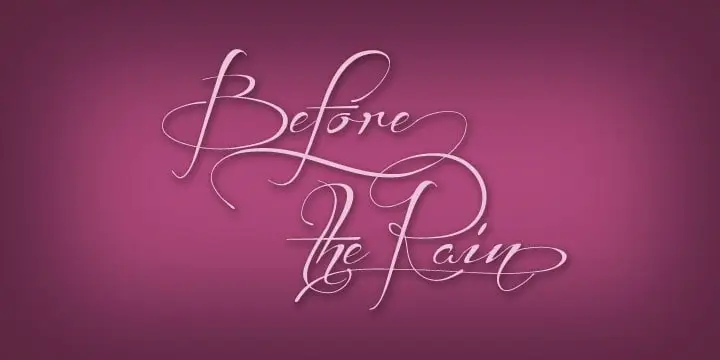
Before The Rain Font – Fonte Grátis
Before The Rain Font
Aqui está uma breve descrição do estilo envolvente e natural da fonte ‘Before The Rain Font’ para a categoria de Script Fonts: Imagine uma fonte de letra script que toca um delicado som de chuva antes de começar. A ‘Before The Rain Font’, criada por Hamilton, é uma composição suave e fluida perfeita para criar letras cheias de emoção. Ela transmite calma e sutileza através da sua forma arredondada e agradável ao olho. Ainda que simplesmente delicada, esta fonte carrega com ela o encanto de uma atmosfera relaxante antes da chegada do sol, ou como se fosse um prelúdio para qualquer tipo de expressão artística. Ideal tanto para criações digitais quanto para trabalho impresso, a ‘Before The Rain Font’ é uma escolha perfeita para aqueles que procuram uma fonte de qualidade para seus trabalhos pessoais e comerciais. Aqui está o endereço onde você pode encontrá-la: http://www.mansgreback.com. Não hesite em entrar em contato  se tiver alguma questão ou interesse em obter uma licença comercial.